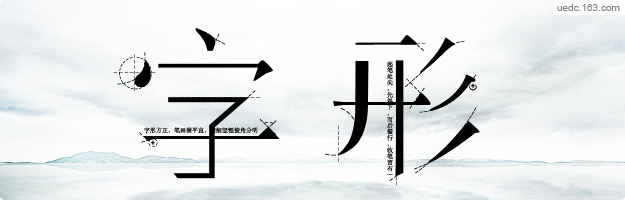
读一本书,看一份报,文字从产生之初就发挥着它不可撼动的地位,充斥着我们每个人每天的生活;然而在繁杂的文字设计中,跳开这些设计,更该去看看最初的文字是什么样子的,珍惜它们每一次的蜕变…
中文字体之宋体
中国文字创造之初,与埃及相同,都是由图画、象形文字演化而来的。但其进化情况却又不同。中国文字的演化,始终维持着原始的绘画或符号内容,只是在形成更多文字时,在原有文字的基础上,加以各种组合,以求形成更多的文字,这在世界文化史上是独一无二的。中国文字的发展,由秦始皇统一中国后,汉字进行了一系列简化,规范化的处理。在木板印刷出现以前,古代典籍为了流传的需要只能手工传抄,由于手工抄写成本高效率底,易出错误,于是木板印刷逐渐盛行。这样,为了刻版方便,渐渐的刻工们发明了一种新字体,它的特点是:字形方正,橫細直粗。在转折处有小三角形装饰。这种字体比楷体更加规范标准,成为了标准字体,适合大规模地刻版使用。这无疑是为了刻书方便从楷体演变出的一种新的字体。由于这种字体大大流行使用于宋朝以后的木版印刷的书籍,后人就称有这种特点的字体为“宋体”。宋体字从历史上出现以后,它的特点就固定了下来,一直使用到现代,直到出现了机械化的印刷工业。在现代印刷中区分更加详细,把横细竖粗的成为“老宋体”。宋体字的字形方正,笔画横平竖直,横细竖粗,棱角分明,结构严谨,整齐均匀,有极强的笔画规律性,从而使人在阅读时有一种舒适醒目的感觉。在现代印刷中主要用于书刊或报纸的正文部分。宋体字传承了中国书法的审美韵味 ,在笔画上,仍然保持了中国书法的本质特征。在与唐楷颜体比较时,我们看得更清楚,如点、捺、撇及转折处的顿挫处理,就是对书法运笔进行了高度的艺术化概括。
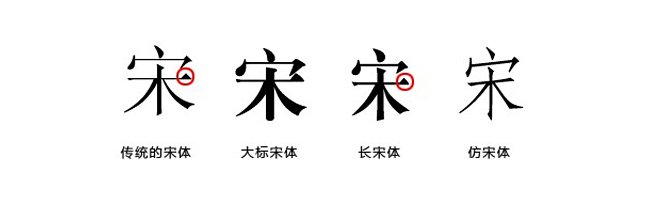
上图4种字体除了第一种最保守的老宋体,其他3种都是衍生出来的宋体字体,我们可以看出前面两种的胸线比较大(字体比较开阔),这是明显的比较现代的字体;而后面两种字体胸线比较小,偏向传统的字体。传统宋体,可以看出,在它身上保留有不少楷体的特征,红色小圈圈里面三角形的鳞(小三角装饰)比较刚硬,是用棱角分明的几何形构成的,虽然给人以严谨的感觉但是让人觉得太过严肃拘谨,所以在现代设计的运用中,大家更偏向于运用其他宋体字形。和传统宋体相比,长宋体的鳞就显得没有那么尖锐了,停笔处依稀可见手笔的停顿转折,看上去圆润了不少。长宋体看上去比一般的宋体要长,也就是刚才说的胸线比较小;它的横、竖粗细相近,点、撇、捺、挑、勾比较挺拔,综合了老宋和仿宋的特点。大标宋,它的特点是横竖笔画对比明显,笔画轻重适中,没有那么硬朗,字形端正,醒目有力,常用于内文标题、封面和广告设计,具有现代感 (类似粗衬线体,后面会提到)。仿宋体,最大特点是横竖等宽”,风格更偏向于手写体,它其实是宋徽宗的瘦金书字体演变而来的,特点是瘦直挺拔,横画收笔带钩,竖划收笔带点,撇如匕首,捺如切刀,竖钩细长;如果说宋体是具有装饰艺术的代表字体,那么与之相对立的就是黑体,黑体的特点就是横线和竖线宽度相等,去除过多的装饰细节,更加简洁。由于当时印刷业的发展,正文部分用的都是宋体,想要突出标题部分从而发展了黑体。
黑体本身就属于比较现代的一种字体,所以它的字面和胸线都比较大,这样比较容易阅读,根据不同需要,设计出横竖笔画不同粗细的黑体字形来,最基本的就是第一种,纤细的黑体字给人轻,秀气的感觉,粗厚的黑体字给人重,粗壮,力量的感觉,这些字形都是根据不同的需要设计而来的。中文字形除了宋体和黑体这两种基本字形以外,还有很多不同种类的,比如
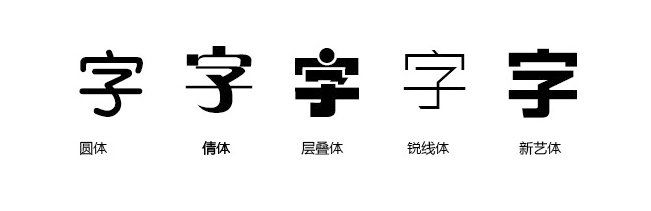
PS:衬线体说法后面会有提到,因为衬线体和无衬线体都是西方字体发展中出现的说法,套用在中文字形中,宋体即是衬线体;黑体即是无衬线体。
英文字体之有无衬线体
西方字母的产生过程,经由埃及→腓尼基→希腊的演变之後,最后在罗马体上集大成,被西方世界广泛运用到现在而风行于全世界。随着活字印刷的产生,在原始罗马体的基础上越来越多的设计师努力创作优美,更易阅读的字体,现在欧洲使用的字母文字,被称为拉丁字母或罗马字母,是世界上应用最广泛的字母。英文字母一般分为衬线体(serif),无衬线体(sans serif)和其他字体。衬线字体,意思是在字的笔画开始、结束的地方有额外的装饰,而且笔画的粗细会有所不同。相反的无衬线体就没有这些额外的装饰,而且笔画的粗细也差不多。现代衬线体出现在18世纪末,强调了粗细笔画之间的强烈对比,加重了竖画,而把衬线做的细长。大部分现代衬线体的可读性不及旧体和过渡衬线体。
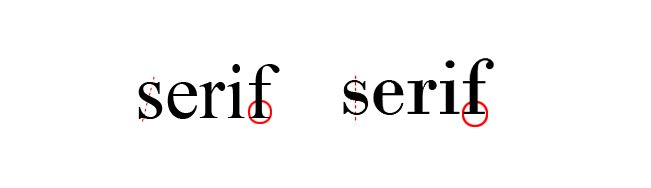
- 衬线体又可分为传统和现代形字体,上图为传统衬线体(左)和现代衬线体(右)
传统衬线体,看S这个字母最细部分,用红色斜虚线标出可以看出它的较细部分始终保持倾斜状态,也就是说笔画的粗细是有变化的,看起来就比较传统,这是一种基本字形。而现代衬线体,笔画粗细始终保重一致的状态,相对比较更加理性,机械,规范化的感觉。再来看底座的支架(我暂且把它叫做支架)传统支架它的笔画连接是弧线的,而现代的就是平直几何形的,这也可以理解为感性与理性的一种对立呈现方式。
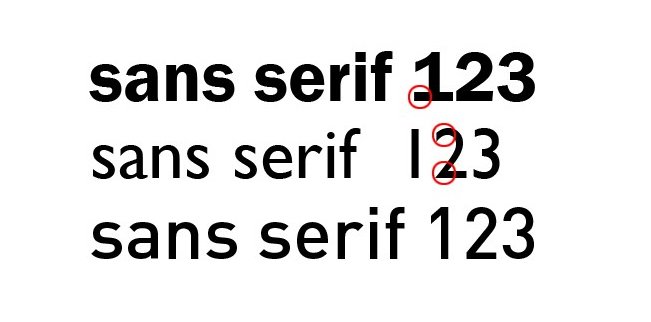
- 无衬线体大致可以分为3类,上图的依次顺序为古典无衬线体,过渡无衬线体,现代无衬线体
古典无衬线体和传统宋体是一样的,最突出的特点就是装饰细节比较多,底部有支架(但是因为它是无衬线体,笔画上不会出现明显的弧度,用的形状比较几何,力量感一点)过渡无衬线字体是介于古典和现代之间的字形,最大的特点就是既有现代感理性简练的感觉也不失感性略带笔触,纤细秀气的感觉。可以看到上图第二个中画红圈部分,它的转角,停顿处是一样的粗细分布。现代无衬线字体的特点是笔画之间粗细很均衡,是理性的象征。
在传统的正文印刷中,普遍认为衬线体能带来更佳的可读性(相比无衬线体),尤其是在大段落的文章中,衬线增加了阅读时对字母的视觉参照。而无衬线体往往被用在标题、较短的文字段落或者一些通俗读物中。但是随着现代生活和流行趋势的变化,如今的人们越来越喜欢用无衬线体,因为他们看上去“更干净”。 在文字足够大的情况下,无衬线字体也是同样可读的。而且因为无衬线字体通常有艺术性,因此在显示器上显示通常比较赏心悦目;而且无衬线字体种类比衬线字体多得多,因此选择余地也很大。
除了有无衬线体之外,还有其他字体:比如一些比较卷曲,贴近自然的巴洛克风手写体,还有一些为了迎合设计风格的变形字体
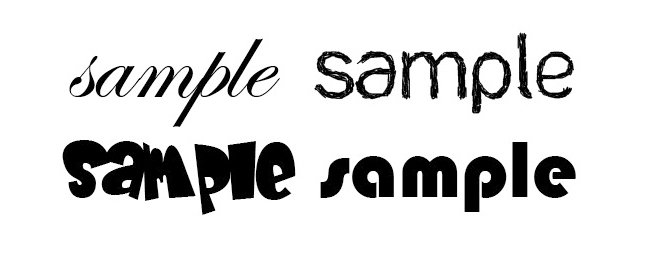
从这些基本字形我们可以发现:文字在发展的过程中,也在不断经历着去繁为简的过程。包豪斯学校的成立,影响了工业产品设计的思维模式,使人们在设计的过程中从以往崇尚自然,繁杂的工艺文化中分离出来,设计在慢慢萌芽,从工业产品到平面艺术,都有所体现。
下面就来看看这些字形在现实生活中的应用:
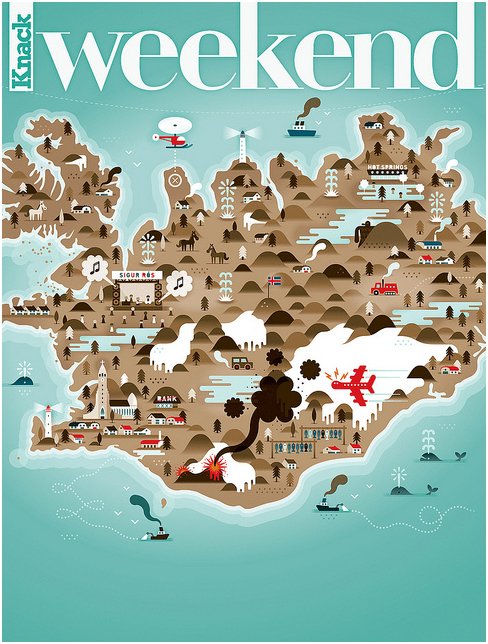
上图中的英文字体是现代衬线体中的一种,“发丝型衬线体”,它的特点是由细致线构成的,看起来非常平整,粗细线条对比清晰,明确,具有现代感。
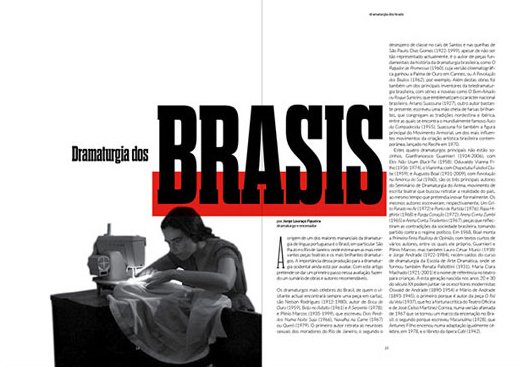
上图标题部分是传统无衬线体的一种字形,画面上体现的是一幅类似传统工业制作的画面,在字体的选用上为了迎合当时的氛围需要,并且能突出主题,选用了粗衬线体,粗旷有力而且很古典。
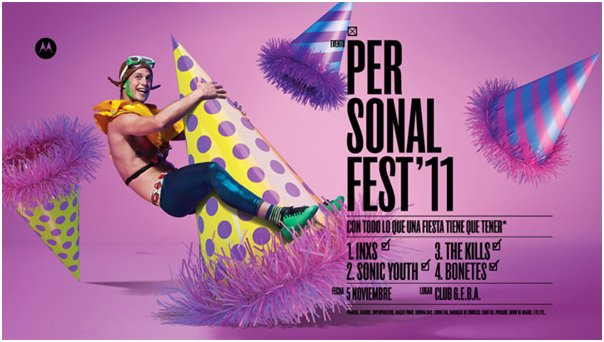
上图标题用的是完全现代的无衬线体字形,版面是横向设计,字体上就选用了比较修长的无衬线体黑体,视觉中心点同样是在中心,和左边的画面有相呼应的细节设计,和字腔较小相呼应的字腔较大字形,比较易读,但是视觉中心点也相对较散一些,人的视线落脚点会比较开阔。
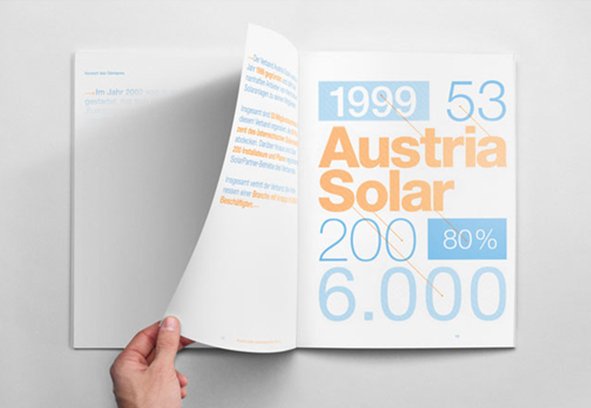
相对上面的字形,这份书籍装帧设计因为它上面仅有文字,所以需要用文字去控制整个版面。在这里,信息层级上最主要的信息选用了较粗的,胸线较大的字体,利用笔画粗细对比去吸引到更多人的关注;两个粗细很极端的字体放一起,用这种对比手法去突出该突出的,弱化该弱化的,但是又不会把空间撑的满满的。
上图这张邀请函上面采用卷曲的手写体,让人感觉非常的亲近,活泼和愉悦。
这是一张日本海报上的字体,中国古代的文字记载就喜欢采用竖排,从右到左进行排列,日本直到现在仍然采用,上图的这种字体有点类似中文宋体中的瘦金书字体,保持它笔画特征的同时,又将它处理地更加圆滑,亲切感自然感增加许多。
这其实是一本李永铨的新书封面,因为他在书中分享自己的成长之途,讲述个人经历或时代背景如何影响他的品牌设计意念,所以封面上出现的应该是他做过的品牌包装。为了迎合整体设计的气质,书名标题没有用力量感过重的粗线形黑体去表现,而是选择了力量适中,看上去纤细适中的中黑;这里也穿插出现了粗细对比的字体;吸引人注意力的同时也十分注重力量的节奏感,不会有强迫阅读感的产生,竖排的设计显得很传统。